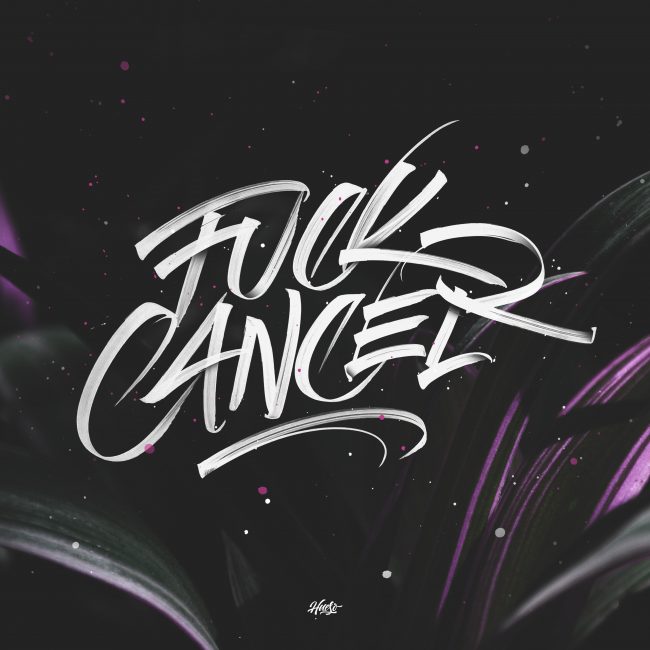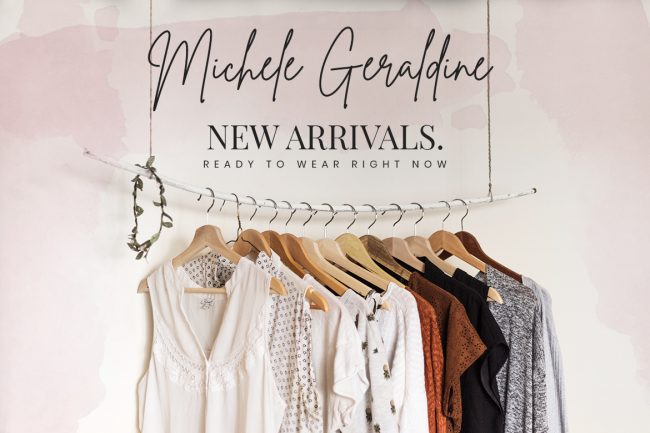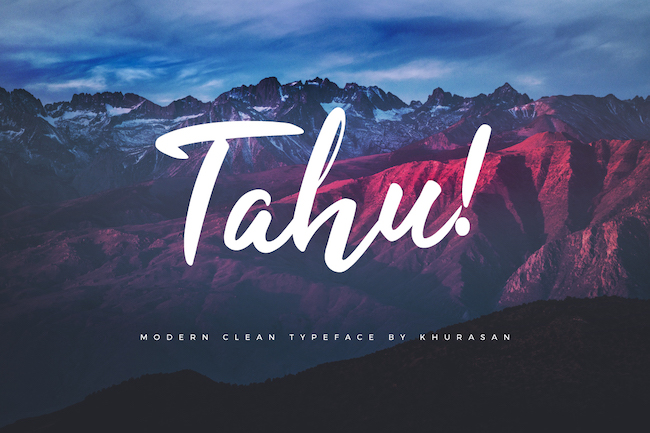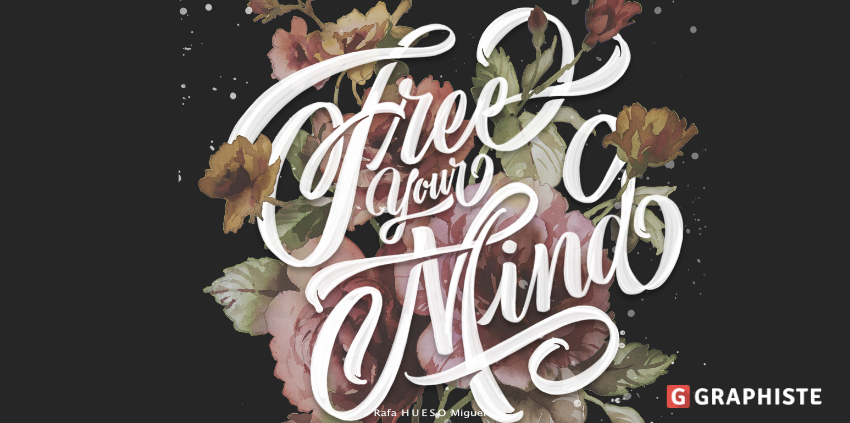
5 conseils pour bien utiliser une typographie manuscrite
Les typographies manuscrites comptent sans doute parmi les plus difficiles à bien utiliser. Parce qu’elles présentent autant de caractéristiques...
Les typographies manuscrites comptent sans doute parmi les plus difficiles à bien utiliser.
Parce qu’elles présentent autant de caractéristiques différentes que l’écriture dite « de médecin » à celle d’une adolescente qui met des cœurs sur ses « i ».
Pour trouver la police de caractère dont vous avez besoin pour votre projet, suivez nos conseils ci-dessous.
1. Insistez sur la lisibilité
Le point le plus important pour une typographie, celui que vous ne soulignerez jamais assez, c’est sa lisibilité. Aussi joli soit-il, si votre texte n’est pas lisible, vous aurez perdu votre temps.
Attention
Ce défi est d’autant plus difficile à relever avec les polices fantaisie ou manuscrites.
Plus la phrase est longue ou le mot peu usité, plus vos lettres doivent ressembler à celles des caractères d’imprimerie. Sinon, la lecture ressemblera trop à un exercice de déchiffrage et peu de personnes ont la patience de Jean-François Champollion.
Ne cherchez pas l’originalité à tout prix.
2. Soyez attentif au message caché
Plus haut, nous parlions des adolescentes qui mettent des étoiles ou des cœurs sur leurs « i ».
Ce type de décoration sera moins attendu de la part d’un avocat d’affaires. Le même style de jugement s’appliquera à la police manuscrite que vous sélectionnerez. Elle sera jugée plus ou moins dynamique, affirmée, enfantine…
Les courbes des lettres, leurs inclinaisons, leurs formes ont un sens… Et vous devrez en tenir compte dans le message que vous voulez faire passer. Vous ne pouvez pas choisir la même typographie dans toutes les circonstances, et c’est encore plus vrai pour les manuscrites.
Fiez-vous à vos premières impressions en ce qui concerne les écritures que vous retenez : vos clients auront sans doute les mêmes.
3. Vérifiez vos accords
Il est assez rare qu’une police manuscrite soit la seule présentée sur un document. Dans la plupart des cas, vous inclurez d’autres éléments textuels (informatifs ou autres).
Or, comme dans tous les cas où vous utiliserez plusieurs typographies, vous devrez vérifier qu’elles s’accordent bien les unes avec les autres.
Attention
Vous aurez ici à faire face à une difficulté supplémentaire : il est possible qu’une police trop carrée, trop rigide, contrebalance trop fermement l’aspect chaleureux et décontracté d’une écriture manuscrite.
Mais il existe heureusement suffisamment de typographies, serif ou sans serif, pour trouver l’accord parfait.
4. Cherchez les polices complètes
Si vous optez pour l’achat d’une typographie existante, vérifiez qu’elle comporte bien tous les éléments dont vous avez besoin… ou dont vous pourriez avoir besoin un jour.
Comme par exemples :
• des chiffres,
• des lettres accentuées,
• des signes de ponctuation…
Tous ces éléments seront utiles : un mot énergique suivi d’un point d’exclamation qui ne lui ressemble pas perd singulièrement de sa force de frappe. Autant vérifier ce détail avant de commencer à utiliser une police de caractères sur tous vos supports de communication !
5. Rendez-la iconique
Il y a les typographies toutes faites, qui s’achètent sur internet. Et celles que vous créez juste pour votre marque. Celles-là peuvent marquer l’Histoire. Ce sera d’autant plus le cas pour un logo, un emblème, un espace bref où vous pouvez véritablement exprimer votre personnalité.
Bon à savoir
Vérifiez juste que l’emblème créé à la main ne se pixellise pas une fois reproduit en grand format. Qu’il soit lisible devient moins important dans le cas d’une signature de marque, même si elle doit rester identifiable.
Si elle ressemble trop à un gribouillis, elle pourra être stylisée tout en conservant son caractère manuscrit. Ce qui permettra aussi de la développer pour l’intégrer à vos prochains visuels.